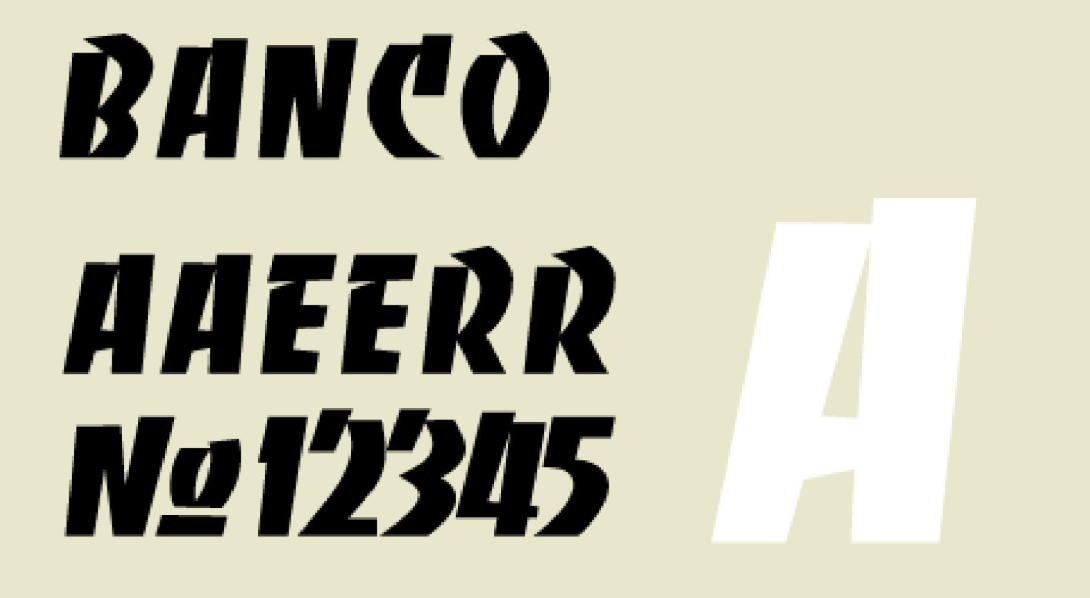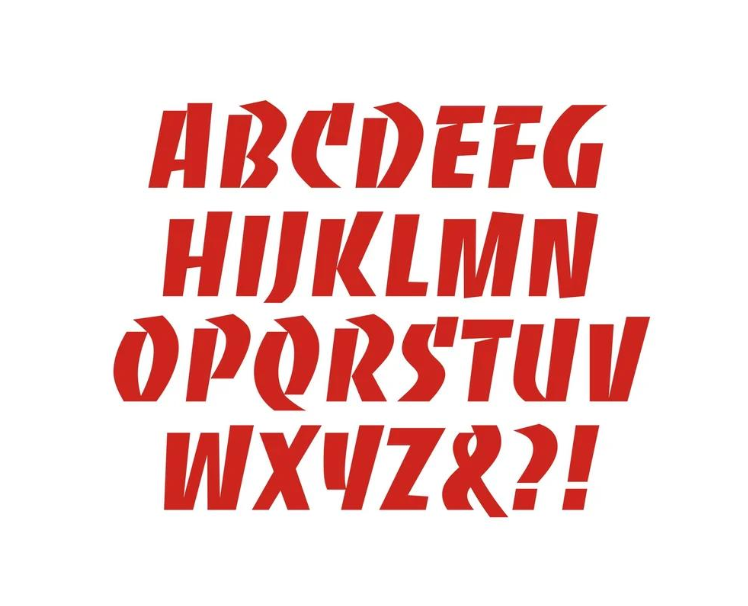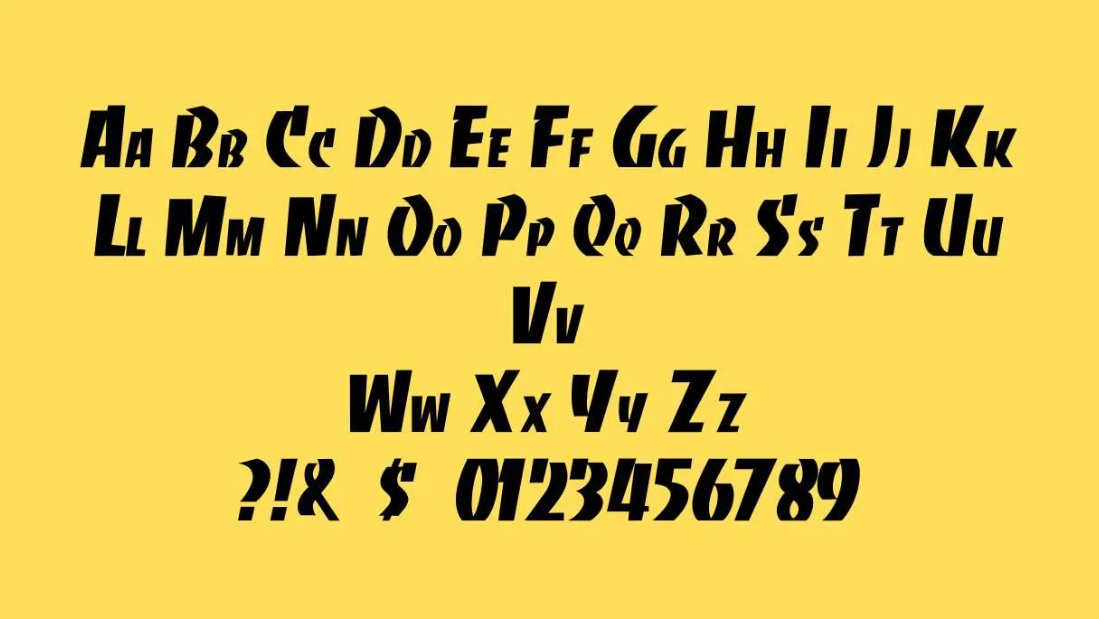
Font Banco Việt hóa là bộ phông chữ Display kinh điển mang tính biểu tượng của đồ họa nước Pháp thế kỷ 20, được sáng tạo bởi bậc thầy Roger Excoffon vào năm 1951 cho xưởng đúc chữ trứ danh Fonderie Olive. Với những đường nét đục đẽo góc cạnh, cấu trúc nét nêm (wedge) dứt khoát và độ nghiêng tràn đầy năng lượng phóng khoáng, Banco đã trở thành huyền thoại trên các bảng hiệu cửa tiệm Paris, bìa album nhạc rock và bao bì sản phẩm thủ công cao cấp. Doozypack.vn cung cấp link tải Font Banco Việt hóa chuẩn kỹ thuật, giúp bạn sở hữu phông chữ độc bản này mà không lo gặp bất kỳ lỗi hiển thị dấu thanh nào khi thiết kế in ấn.
Đặc điểm thẩm mỹ độc đáo của bộ font Banco
Banco không đi theo sự tròn trịa hay quy chuẩn ngay ngắn của các phông chữ hình học; nó mang đến một ngôn ngữ thị giác đầy tính điêu khắc, hoang dã và đậm đà phong vị Địa Trung Hải.
Di sản thiết kế từ bậc thầy Roger Excoffon thế kỷ 20
Đặc trưng lớn nhất của Font Banco Việt hóa là các con chữ được tạo hình như những nhát đục dứt khoát trên khối đá hoặc phiến gỗ cứng. Cấu trúc chữ sở hữu độ tương phản ngược độc đáo, các nét chữ dày dặn ở phần trên và thuôn nhọn dần xuống dưới tạo nên trọng tâm thị giác vô cùng phá cách. Khi đặt Banco làm tiêu đề trên bao bì, thương hiệu của bạn sẽ ngay lập tức toát lên vẻ thô mộc, cá tính mạnh mẽ và khẳng định bản sắc thủ công tinh xảo.
Đường nét đục đẽo góc cạnh đầy uy lực và giàu năng lượng
Các ký tự của Banco được thiết kế chủ yếu ở định dạng chữ in hoa (All-caps style) với độ nghiêng nhẹ về phía trước, tạo cảm giác chuyển động và nhiệt huyết không ngừng. Từng góc cắt vát sắc lẹm giúp tiêu đề bản thiết kế giữ được sự vững chãi, uy quyền và rất dễ nhận diện từ khoảng cách xa trên các kệ hàng trưng bày.
Ưu điểm nổi bật của bản Font Banco Việt hóa
Khi ứng dụng các phông chữ có cấu trúc góc cạnh độc đáo vào thị trường trong nước, sự chỉn chu về dấu câu là yếu tố quyết định đến tính chuyên nghiệp của ấn phẩm:
- Khắc phục triệt để lỗi dấu tiếng Việt: Phiên bản Việt hóa đã được đội ngũ thiết kế trau chuốt thủ công từng dấu câu. Các dấu sắc, huyền, hỏi, ngã, nặng được vẽ với các góc vát và độ dày nét nêm hoàn toàn ăn khớp cùng thân chữ gốc, không gây cảm giác chắp vá hay đè nét làm mất tính thẩm mỹ điêu khắc.